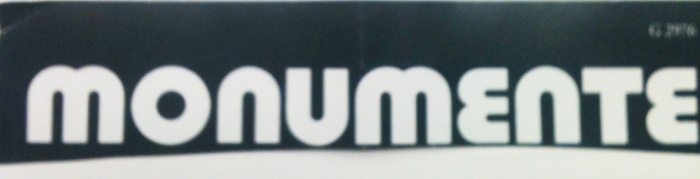
Bauhaus, aber etwas anders gesucht
Ich komm nicht drauf, wie diese Schrift heißt: ich finde sie zwar blöd, aber die Kundschaft besteht drauf. Weiß jemand hier, was das ist? Irgendwas in Richtung Bauhaus isses, aber dieses E und dieses T ist natürlich anders ...
Ich meine diese Schrift hier auch schonmal in irgendeiner Anfrage gesehen zu haben, finde sie aber nicht wieder.